这些字体设计也太!好!看!了!吧!
汉字,历史悠久,在中国亦称中文字、国字、唐字、方块字,是世界上独有的一种指示会意文字体系。作为汉语或中文的书写文字,汉字是迄今为止连续使用时间最长的主要文字,也是上古时期各大文字体系中唯一传承至今的。汉字也被借用于书写日语、朝鲜语、越南语等语言,是汉字文化圈广泛使用的一种文字。
汉字的魅力在于其独特的字符结构,从而在视觉层面上我们能够直观感受到每个字独有的表情和性格。西文字体需要通过单词与单词之间的组合继而形成词汇来传达意思,而汉字却能够从每一个独立的字符中传递出自身所专属的个性。
当设计师在对汉字字体进行设计时,需要不断地对字体进行解构和创作,以此寻求作品在设计中的独创性。除了需要注重“独创性”这个特点,我们还需要了解每一个汉字及其组合起来所代表的涵义。如果能在字体设计中呈现出上述特征,那么这样的作品无疑是能打动人的。
今天我们将为大家带了几位新晋日本字体设计师的作品,每一件作品都像一个故事一样精彩;每一个字符,都如一幅画一样有趣。
①
nozaki azusa
日本字体设计师,
专注于字体图形设计及网页设计
nozaki azusa,一位非常年轻的90后日本字体设计师,其字体设计作品有一个明显的特点就是“有趣”,每一个字体创作都如同一幅画一样,设计师在对字体进行创作的时也会根据其字面表达的涵义,将设计理念融入其中。不得不感慨,拥有创造力,能让传统汉字字符充满活力。
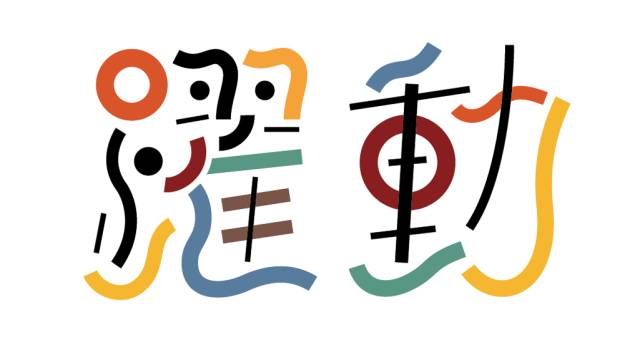
躍動
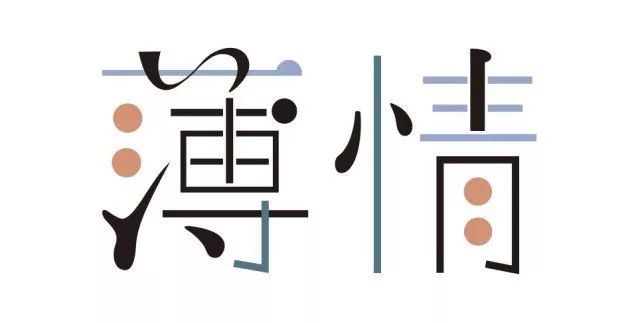
薄情
逃走
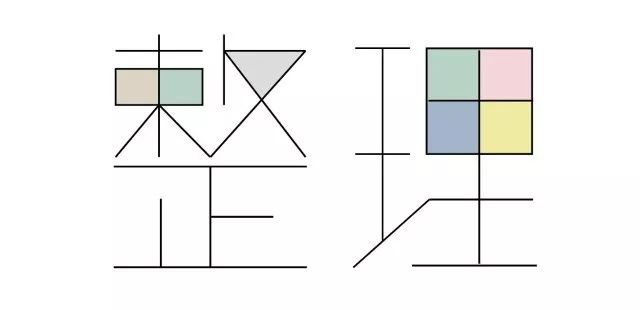
整理
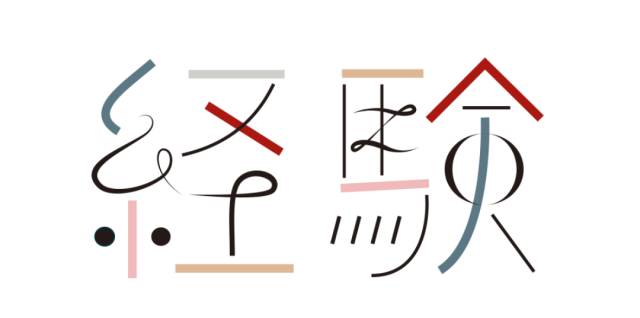
經驗
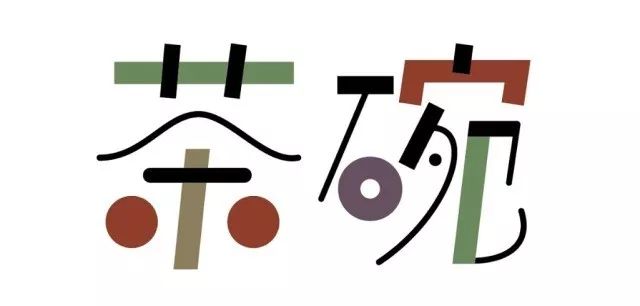
茶碗
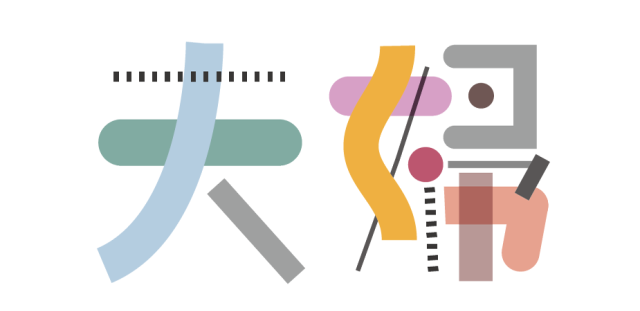
夫婦
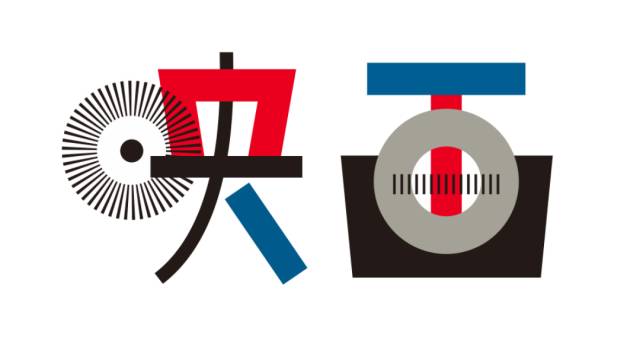
映画
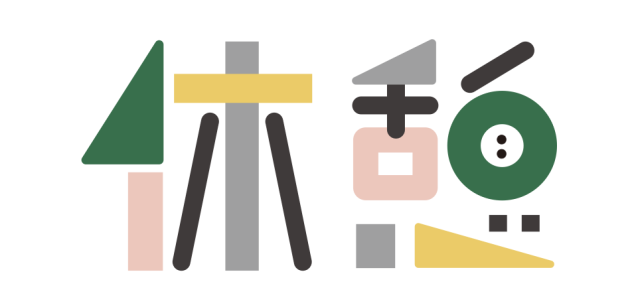
休憩
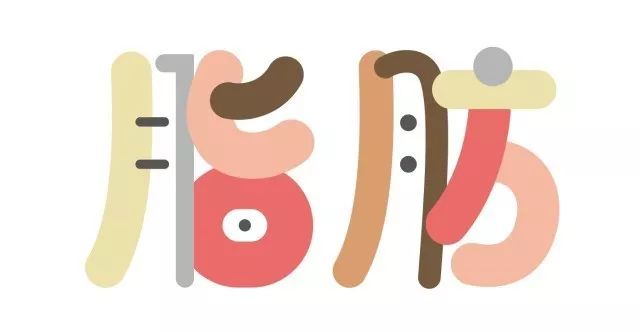
脂肪
田舍
冬
②
MIENO RYU
三重野龙
日本平面设计师
MIENO RYU(三重野龙)毕业后开始自由职业工作者的身份,其不羁的设计风格及肆意洒脱的作品让人过目不忘。汉字在他手中变成了一种传达自我和性格的表现形式。
Post
海报系列
MUSUBU SHIGA 空想 MUSEUM
group exhibition WHO
村の芸術祭
芸能山城組
青銅の交響楽
山下拓也個展
弱弱様
知らない都市 INSIDE OUT
标志系列
③
kwkm
日本字体设计师
kwkm同样是位非常年轻的日本字体设计师,如果说三重野龙的作品非常的随性、不羁,那么kwkm的作品则是充斥着满满的少女心!可爱的插画搭配不带有冲击性的字体设计,一眼过去,觉得整体画面很是协调,非常舒服。
季節の晩餐会 芽吹きの春編
少女都市 「光の祭典」flyer design
なんちゅうか中華
程無く泣く程
季節の隙間に横たわる
冬は浮遊
雨天決行で結構